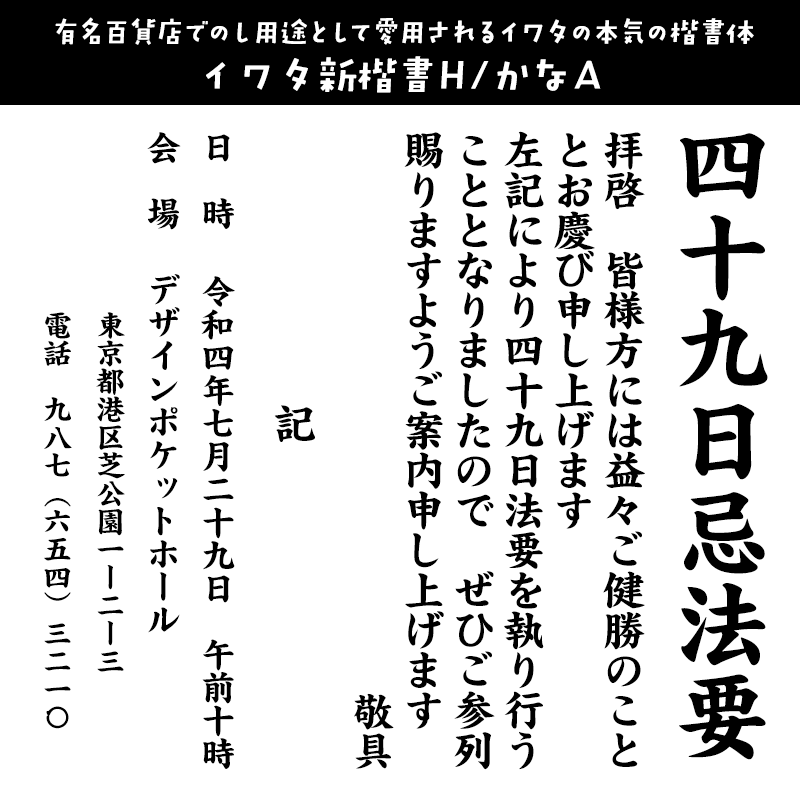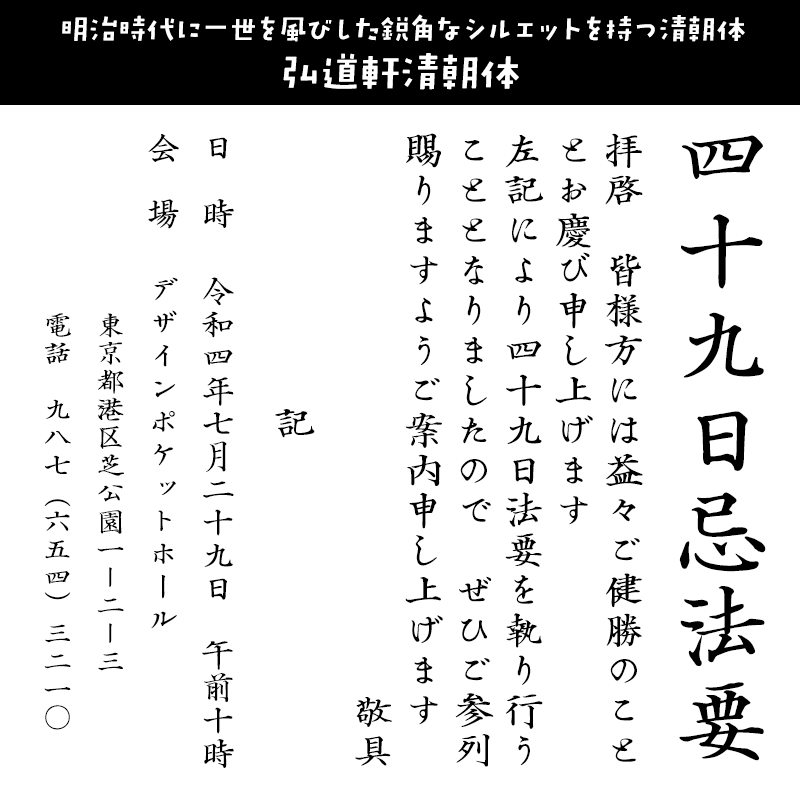
冠婚葬祭に合うフォント:特化型 目的別フォントガイド #062
冠婚葬祭に合うフォントをスタッフが選びました
冠婚葬祭に合うフォント モトヤ新楷書3
格調高く美しいフォント。現代的な字形の楷書で読みやすい。
モトヤ新楷書3【モトヤ】
冠婚葬祭に合うフォント モトヤ新楷書3
モトヤ正楷書の「糸偏」と「草冠」を現代的な字形にし、主にご婚礼や教育の場での使用を目的とした楷書体です。
冠婚葬祭に合うフォント 丸明オールド
フォーマルにピッタリな優しさのある上品な明朝体
丸明オールド【砧書体制作所】
冠婚葬祭に合うフォント 丸明オールド
サントリーモルツ・シャープAQUOSなどで有名な書体。縦線、横線、点、トメ、ハライなどどれも先端が丸く処理されています。
冠婚葬祭に合うフォント 丸明Katura
文字を構成するエレメントに丸を使っている不思議な可読性を持った書体
丸明Katura【砧書体制作所】
冠婚葬祭に合うフォント 丸明Katura
明朝体にも丸明朝体というカテゴリーがあることを実証した書体。フォーマルさを残しながらも味のある明朝書体です。
冠婚葬祭に合うフォント 極 (白舟極太楷書/行書/草書/隷書セット)
ハッキリとした骨格にドッシリとした力強い筆遣いがインパクト大!
極 (白舟極太楷書/行書/草書/隷書セット)【白舟書体】
冠婚葬祭に合うフォント 極 (白舟極太楷書/行書/草書/隷書セット)
成人式・結婚式の案内状やお祝い状などの書面でも大活躍します。「極(きわみ)」は、極太きわめた四天王、白舟極太楷書・極太行書・極太草書・極太隷書の4書体セットです。
※このサンプルは白舟極太楷書を使用しています
冠婚葬祭に合うフォント TAS-香蘭
女流書家による繊細で洗練された毛筆書体
TAS-香蘭【スキルインフォメーションズ】
冠婚葬祭に合うフォント TAS-香蘭
女流作家、香蘭のデザイン毛筆。繊細な筆文字を再現。洗練された筆文字の魅力あふれる書体で冠婚葬祭・フォーマルなシーンに最適な毛筆書体です。
冠婚葬祭に合うフォント イワタUD明朝 かなB
現代的でラインを意識したデザインが特徴の明朝書体。
イワタUD明朝 かなB【イワタ書体ライブラリー】
冠婚葬祭に合うフォント イワタUD明朝 かなB
見やすさに重点を置いて開発されたUDデザインの明朝体。現代的でラインを意識したデザインが特徴。招待状などにぴったりのフォントです。
冠婚葬祭に合うフォント DF古籍銀杏
優雅さ、美しさを持つフォーマルな印象を持つ古籍書体
DF古籍銀杏【ダイナフォント】
冠婚葬祭に合うフォント DF古籍銀杏
中国の古籍「天工開物」をモチーフとして開発された書体です。「天工開物」の文字は、半円形となったストロークが繊細で、銀杏の葉っぱのような優雅さがあります。文字の重心が高く穏やかで、文字を読む際にイチョウ並木にいるような視覚的な美しさが感じられます。
冠婚葬祭に合うフォント イワタミンゴ
明朝体とゴシック体の良いところを併せ持つシャープで読みやすいフォント
イワタミンゴ【イワタ書体ライブラリー】
冠婚葬祭に合うフォント イワタミンゴ
2015 年にグッドデザイン賞を受賞した「イワタミンゴ」は、明朝体とゴシック体の良いところを併せ持つデザイン、ディスプレイでの読みやすさを目的に開発され、シャープでモダン。そしてスッキリと読みやすく冠婚葬祭・フォーマルな場でもピッタリの書体です。
冠婚葬祭に合うフォント イワタ新楷書H/かなA
有名百貨店で熨斗用途として愛用されるイワタの本気の楷書体
イワタ新楷書H/かなA【イワタ書体ライブラリー】
冠婚葬祭に合うフォント イワタ新楷書H/かなA
書の概念を取り入れ「力強く」「伸びやかな」新しい感覚の特太楷書体です。 縦組みでも横組みでもお使いいただけます。「整然とし、読みやすい」『イワタ新楷書』は、見出しに限らず文字サイズの小さな部分にも、無理なくお使いいただける万能な楷書体です。
冠婚葬祭に合うフォント 弘道軒清朝体
明治時代に一世を風靡した鋭角なシルエットを持つ清朝体
弘道軒清朝体【イワタ書体ライブラリー】
冠婚葬祭に合うフォント 弘道軒清朝体
日本で一番古い部類の金属活字楷書体をデジタル化したフォントです。活字の父型は鋼鉄の角棒に文字を直彫りする豪快な手法で作成され、鋭角なシルエットを持つ独特な書体です。フォーマルなシーンでも活躍する書体です。
冠婚葬祭に合うフォント DF行書体
流麗な印象のフォーマルな行書体。
DF行書体【ダイナフォント】
冠婚葬祭に合うフォント DF行書体
書を嗜める際の筆の動きや感情を一画ごとに表現した書体。文字の続け書きによる画法は躍動感を感じさせてくれます。喪中はがき等の裏面や宛名の書体としておすすめです。
冠婚葬祭に合うフォント イワタ楷書体
伝統的な毛筆の味わいを表現した筆書系書体。
イワタ楷書体【イワタ書体ライブラリー】
冠婚葬祭に合うフォント イワタ楷書体
毛筆の味わいを表現し、くせがなく・親しみやすく・読みやすいデザイン。冠婚葬祭の幅広い案内状で使える汎用性の高いフォントです。
冠婚葬祭に合うフォント DF金文体 Pro-6N W5
神秘性や独創性などを高めた、個性があふれるフォント。
DF金文体 Pro-6N W5【ダイナフォント】
冠婚葬祭に合うフォント DF金文体 Pro-6N W5
家族葬や生前葬を行うためのご案内状・会葬礼状などの見出しにもお使いいただけます。「DF金文体」は、殷・周・秦時代に青銅器に鋳込み刻まれた文字「金文」をモチーフにした書体です。
冠婚葬祭に合うフォント あけぼの書体
細めで美しいフォーマルな文書にぴったりの毛筆書体
あけぼの書体【昭和書体/コーエーサインワークス】
冠婚葬祭に合うフォント あけぼの書体
細めですが部分部分にしっかりしたラインを持った書体です。賞状、感謝状、挨拶状などの冠婚葬祭・フォーマルな文書に使いやすい毛筆書体です。
冠婚葬祭に合うフォント KOさおとめ金陵
1つは持っておきたいフォーマルに使える明朝体
KOさおとめ金陵【欣喜堂】
冠婚葬祭に合うフォント KOさおとめ金陵
冠婚葬祭など、フォーマルや堅い文章にピッタリはまる明朝体。美しいさの中に少しの個性が光る、可読性抜群のフォントです。